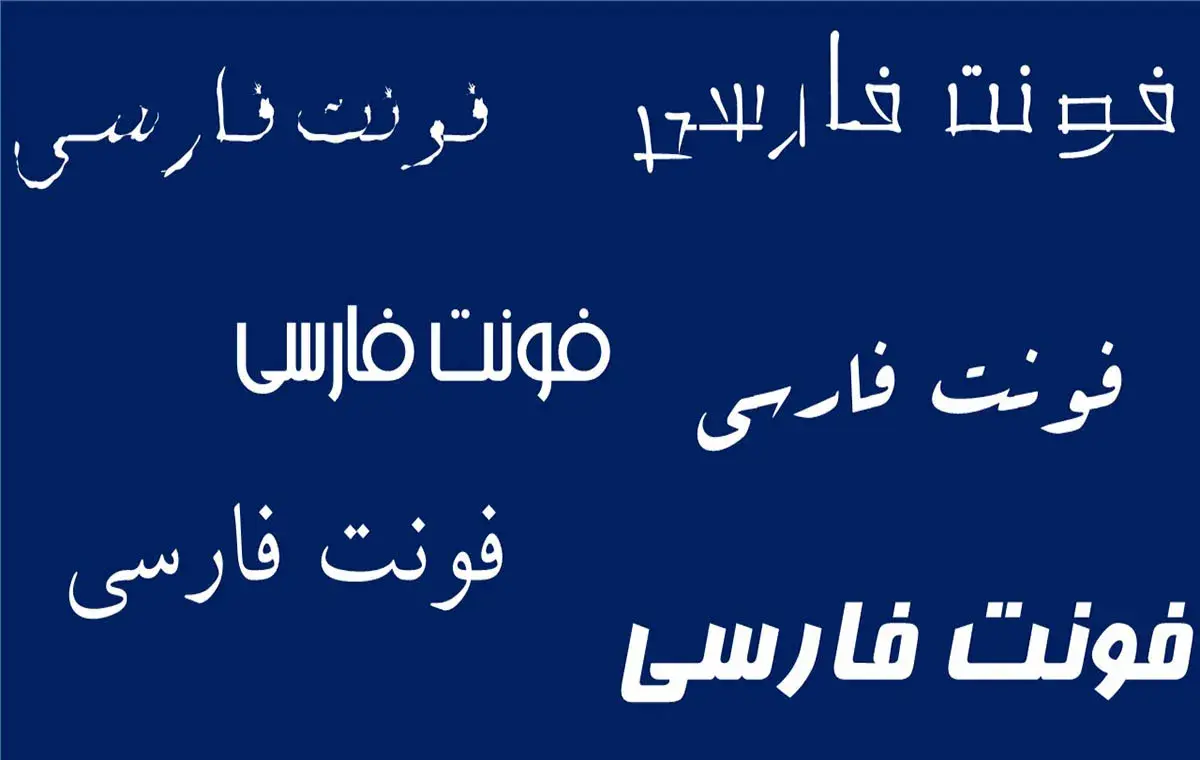
بهترین فونتهای فارسی برای تولید محتوا
برای موفقیت در تولید محتوای فارسی، توجه به جزئیاتی مانند فونت اهمیت زیادی دارد؛ زیرا فونت مناسب نهتنها بر زیبایی ظاهری محتوا تأثیر میگذارد، بلکه در درک بهتر پیام، جذب مخاطب و ایجاد اعتماد نیز نقش دارد. فونتهایی مانند «وزیر»، «ایرانسنس» و «شبنم» از گزینههای رایگان و پرکاربردی هستند که به دلیل طراحی مدرن، خوانایی بالا و سازگاری با محتوای دیجیتال، محبوبیت زیادی یافتهاند. در ادامه مطلب، فهرستی از بهترین فونتهای فارسی برای تولید محتوا با کاربردهای مختلف ارائه شده تا کاربران بتوانند با دقت و آگاهی، فونتی متناسب با پیام محتوای خود انتخاب کنند.
معیارهای انتخاب بهترین فونتهای فارسی برای تولید محتوا
در فرآیند تولید محتوای فارسی، انتخاب فونت از آن دسته تصمیماتی است که در ظاهر ساده به نظر میرسد، اما در عمل تاثیر بسیار عمیقی بر کیفیت نهایی محتوا و تجربه مخاطب میگذارد. فونت نقش به سزایی در زیباییشناسی، ارتباطی و حتی روانی مخاطب دارد. بسیاری از مخاطبان قبل از آنکه مفهوم متن را درک کنند، ناخودآگاه با ظاهر آن ارتباط برقرار میکنند. بنابراین فونتی که انتخاب میکنید باید بتواند بهدرستی و با دقت، روح و لحن محتوای شما را بازتاب دهد.
یکی از اساسیترین معیارهای انتخاب فونت، وضوح و خوانایی بالا است. در دنیایی که کاربران اغلب با چشم خسته، در محیطهای پرنور یا با اسکرینهای کوچک در حال مطالعه هستند، فونتی که ساختار واضح، ضخامت مناسب خطوط، فاصله مناسب بین حروف و سطرها و چشمنواز بودن را داشته باشد، مزیتی بزرگ محسوب میشود. فونتهایی که بیش از حد تزئینی، فشرده یا سبک هستند، حتی اگر زیبا باشند ممکن است باعث رها شدن متن شوند.
معیار مهم بعدی، هماهنگی سبک فونت با محتوای ارائهشده است. مثلا اگر در حال نگارش یک مقاله علمی، خبری یا حقوقی هستید، فونتی با فرم رسمی و متقارن که حس اعتماد و جدیت القا میکند، بهترین انتخاب است. اما اگر محتوای شما آموزشی، سرگرمکننده یا روزمره باشد، فونتی با ساختار سادهتر، منحنیهای ملایمتر و حالوهوای خودمانیتر، تعامل بهتری با مخاطب ایجاد خواهد کرد. این تطابق ظریف میان سبک نوشتاری و شکل نوشتار، اغلب نادیده گرفته میشود اما تاثیر مهمی بر ماندگاری برند یا پیام دارد.
علاوه بر این، فونت انتخابی شما باید در فضاهای مختلف به درستی عمل کند. این یعنی چه در موبایل، چه در تبلت، چه در مانیتورهای بزرگ، فونت دچار شکستگی، جابهجایی یا تغییر ساختاری نشود. همچنین اگر محتوا قرار است چاپ شود، باید از فونتی استفاده شود که در نسخه چاپی هم کیفیت، نظم و خوانایی لازم را حفظ کند. نکتهای که در فضای دیجیتال بسیار مهم است، عملکرد فونت در حجمهای بالا و در فواصل طولانی متن است. برخی فونتها در عناوین خوب بهنظر میرسند اما در پاراگرافهای طولانی خستهکنندهاند.
نکته قابل توجه دیگر، هویت بصری برند یا محتوا است. فونت بخشی از شخصیت گرافیکی شماست. اگر تولید محتوای شما در بستر مشخصی انجام میشود ـ مثلا یک پیج اینستاگرامی با لحن خاص یا یک وبسایت رسمی ـ بهتر است فونتی را انتخاب کنید که با بقیه عناصر گرافیکی شما مثل رنگها، آیکونها و حتی لوگو همخوانی داشته باشد. یک فونت هماهنگ، باعث انسجام تصویری میشود و مخاطب را ناخودآگاه به برند یا محتوای شما وفادارتر میکند.
همچنین نباید از اهمیت جزئیات طراحی فونت غافل شد. کیفیت خط کرسی، دقت در طراحی حروف خاص فارسی مانند «ک» و «ی»، شکل نقطهها، نحوه اتصال حروف و حتی وضعیت کشیدهنویسی یا نسخههای بولد و نازک، همه در تاثیرگذاری بصری آن نقش دارند. فونتی که از نظر طراحی حروف متعادل و دقیق باشد، میتواند به افزایش تمرکز خواننده کمک کند و انتقال پیام را به شکل کاملتری انجام دهد.
در کنار این نکات، انتخاب فونت باید بر پایه تجربه کاربری واقعی صورت بگیرد، نه فقط ظاهر اولیه آن. گاهی ممکن است فونتی در نگاه اول جذاب باشد، اما وقتی در متنهای طولانی یا در انواع تیتر و زیرتیتر استفاده شود، مشکلاتی مانند سنگینی بصری، تکرار خستهکننده یا سختخوان بودن را نشان دهد. بنابراین پیش از انتخاب نهایی، بهتر است فونت را در کاربردهای واقعی امتحان کنید.
در نهایت باید گفت که فونت، بخشی از زبان تصویری محتواست. همانطور که نوع جملهبندی، لحن و سبک نوشتاری شما حامل پیام است، شکل و فرم نوشتار هم پیام مستقلی دارد. فونتی که با دقت انتخاب شده باشد، میتواند حس اعتماد، صمیمیت، هیجان یا حتی آرامش را منتقل کند؛ بدون آنکه حتی یک کلمه حرف بزند. انتخاب درست فونت، یک مهارت مهم در طراحی محتواست که نیاز به دقت، سلیقه و شناخت دقیق از هدف محتوا و مخاطب دارد.
بهترین فونتهای فارسی برای تولید محتوا؛ وزیر
فونت وزیر یکی از معروفترین و بهترین فونتهای فارسی برای تولید محتوا است که توسط مرحوم صابر راستی کردار طراحی شده است. این فونت با الهام از فونتهای مدرن لاتین طراحی شده و ویژگی بارز آن، سادگی و نظم در ساختار حروف است. در فونت وزیر، هر حرف جای خودش را بهخوبی پیدا کرده است؛ فاصلهها استاندارد هستند و خوانایی آن در ابعاد مختلف بسیار بالاست. یکی از مزایای مهم وزیر این است که در صفحات وب بهخوبی رندر میشود و به همین دلیل در بسیاری از وبسایتهای حرفهای، بلاگها و صفحات طولانی محتوایی از آن استفاده میشود. این فونت از نسخههای نازک تا ضخیم پشتیبانی میکند و در تایپوگرافی دیجیتال، قدرت انعطاف بالایی دارد. حتی در استفاده در نرمافزارهای آفیس یا فتوشاپ هم عملکرد بسیار خوبی دارد.
بهترین فونتهای فارسی رایگان برای تولید محتوا؛ شبنم
فونت شبنم از دیگر گزینههای رایگان و قابل اتکا در فضای تایپ فارسی است. طراحی آن کمی رسمیتر و سنگینتر از وزیر است، اما همچنان حال و هوای مدرن دارد. شبنم بهخصوص در تیترها عالی عمل میکند؛ حروف آن کمی پهنتر و ضخیمتر هستند و در سایزهای بزرگتر بهتر به چشم میآید. این فونت ترکیبی از رسمی بودن و صمیمیت را در دل خود دارد، به همین دلیل در طراحی وب، مجلات دیجیتال، بروشورها و حتی اینفوگرافیها میتواند انتخاب خوبی باشد. از آنجایی که شبنم تعادل مناسبی میان فرم و خوانایی دارد، میتوان آن را در هر دو حالت چاپی و دیجیتال با خیال راحت استفاده کرد.
بهترین فونتهای فارسی برای تولید محتوا؛ صمیم
فونت صمیم از نظر احساسی یکی از دلپذیرترین فونتهای فارسی است. خطوط منحنی، گوشههای گرد و فضای باز بین حروف، باعث شده این فونت حس نزدیکی و راحتی را منتقل کند. اگر در حال تولید محتوایی هستید که قرار است رابطهای دوستانه با مخاطب ایجاد کند، مثلا محتواهای آموزشی، خانوادگی، کودکمحور یا شبکههای اجتماعی، فونت صمیم انتخاب فوقالعادهای است. این فونت در اپلیکیشنهای موبایلی هم بهخوبی عمل میکند چون فرم آن برای مطالعهی طولانی مناسب است و در نمایشگرهای کوچک هم خواناست. صمیم نشان میدهد که فونت فقط مسئلهی زیبایی نیست، بلکه میتواند در لحن محتوا هم تاثیرگذار باشد.
بهترین فونتهای فارسی برای تولید محتوا؛ ساحل
فونت ساحل ساختاری شبیه به شبنم دارد، اما از نظر بصری کمی سبکتر است. این فونت نه خیلی رسمی است و نه خیلی خودمانی؛ یک تعادل کاربردی برای موقعیتهای مختلف دارد. از آن در طراحی سایت، ارائههای رسمی، محتوای شرکتی یا حتی طراحی بروشورها میتوان استفاده کرد. ویژگی مهم ساحل، ظاهر تمیز و ساده آن است. از آنجایی که حروف این فونت زاویهدارتر و دقیقتر طراحی شدهاند، برای پروژههایی که دقت و نظم بصری مهم است، گزینه خوبی خواهد بود. در عین حال، ضخامت مناسب خطوط آن اجازه میدهد تا در تیترهای واضح یا متون برجسته هم از آن بهره گرفت.
بهترین فونتهای فارسی برای تولید محتوا؛ دیناربیک
فونت دیناربیک یکی از فونتهایی است که ظاهری امروزی و سیستماتیک دارد. ساختار این فونت مستطیلیتر است و از خطوط صاف و شکسته بیشتری استفاده میکند. در نتیجه، فرمی مهندسیوار و فنی به خود گرفته که برای پنلهای مدیریتی، رابط کاربری وبسایتها، داشبوردهای دیجیتال یا هر محیطی که نیاز به نمایش دقیق اطلاعات وجود دارد، عالی عمل میکند. دیناربیک همچنین در پروژههایی که با داده، آمار یا تکنولوژی سر و کار دارند، حس مدرنیته و نظم را منتقل میکند. طراحی حروف آن بهگونهایست که در محیطهای پرمحتوا با فونت کوچک همچنان شفاف و قابل خواندن باقی میماند.
بهترین فونتهای فارسی برای تولید محتوا؛ ایران یکان
فونت ایران یکان و نسخههای مشابه آن هم از جمله فونتهایی هستند که فرم خاص خود را دارند. این فونت مینیمال، ساده و بسیار مدرن طراحی شده و در برندهای حرفهای، اپلیکیشنهای موبایل و طراحیهای گرافیکی بهشدت کاربرد دارد. ویژگی بارز آن، عدم استفاده از تزئینات اضافی، فاصلههای متوازن و یکدستی بالا بین خطوط و حروف است. فونتهای رایگان مشابه ایرانیکان هم از همین اصول طراحی پیروی میکنند و اگرچه بعضا در کیفیت به آن نمیرسند، اما برای پروژههایی که نمیخواهند هزینه پرداخت کنند، جایگزینهای خوبی به حساب میآیند. این سبک فونت برای کسبوکارهای استارتاپی، فروشگاههای آنلاین و رابطهای کاربری دیجیتال، ایدهآل است.
بهترین فونتهای فارسی برای تولید محتوا؛ نوتو
فونت نوتو نسخ فارسی توسط گوگل منتشر شده و یکی از فونتهای بسیار سبک، منظم و خواناست. طراحی آن بر اساس شیوهی سنتی نسخ انجام شده، اما برای استفاده در محیطهای دیجیتال بهینهسازی شده است. از آنجایی که گوگل پشت این فونت است، میتوان از سازگاری بالا، اجرای روان در مرورگرها و وضوح بینقص آن مطمئن بود. در متون طولانی، مقالات علمی، سایتهای خبری یا بخشهای بلاگ بسیار عملکرد خوبی دارد و چون از نظر فنی بسیار سبک است، در صفحات پرمحتوا باعث افزایش سرعت لود هم خواهد شد.
بنان
فونت بنان را میتوان یکی از فونتهای خاص و خلاقانه در تایپ فارسی دانست. حروف این فونت حالتی هنری دارند و با خلاقیت طراحی شدهاند، بهطوریکه حالت هندسی و حتی کمی نامتعارف دارند. بنان برای محتواهایی که دنبال تمایز هستند کاربرد دارد: مثلا طراحی جلد کتاب، پوسترهای کودکانه یا طرحهایی که قرار است حس کنجکاوی، شور یا هیجان را منتقل کنند. البته استفاده مداوم از آن در متنهای زیاد توصیه نمیشود، چون ممکن است چشم را درگیر و ذهن را از محتوا دور کند، اما برای طراحی بصری و نوآورانه جای خود را دارد.
نیریزی
فونت نیریزی یکی از فونتهای خاص و خوشساخت در میان فونتهای فارسی است که بر پایهی زیباییهای خوشنویسی نسخ و ثلث طراحی شده است. حروف در این فونت بلند، کشیده و پر از جزئیاتاند. ضخامتها در آن متغیر هستند و حرکت خطی حروف حالتی شبیه به نوشتار سنتی دارد. نیریزی بهویژه در پروژههایی کاربرد دارد که میخواهند حس رسمی، تاریخی یا فرهنگی منتقل کنند. اگر در حال طراحی بروشورهای مذهبی، بنرهای فرهنگی یا مقالات با لحن جدی هستید، این فونت با جلوهی سنگین و رسمیاش انتخابی هنرمندانه خواهد بود. البته استفاده از آن در متنهای طولانی دیجیتال توصیه نمیشود، چرا که بیش از اندازه جلوه دارد و تمرکز مخاطب را از محتوا دور میکند.
فرهود
فونت فرهود ترکیبی از صراحت و ظرافت است. طراحی آن بهنوعی میان فونتهای چاپی قدیمی و تایپهای مدرن فارسی ایستاده به حساب میآید. حروف در این فونت حالتی نرم دارند، اما در عین حال رسمالخط آن دارای ساختار استوار است. فرهود بیشتر در پروژههایی کاربرد دارد که به دنبال یک بیان ادبی یا فرهنگیاند؛ مثلا در صفحات کتاب، جلد رمانها، بروشورهای فرهنگی یا محتوای مرتبط با ادبیات و تاریخ. این فونت حس احترام، وقار و دقت را به خواننده منتقل میکند و اگر با فاصلهگذاری مناسب استفاده شود، میتواند تجربهی خواندن دلپذیری هم فراهم کند.
ایرانسنس
فونت ایرانسنس یکی از مشهورترین و پراستفادهترین فونتهای فارسی مدرن در سالهای اخیر است. این فونت بهصورت رسمی پولی است، اما نسخههایی از آن در دسترس عموم قرار گرفته است. حروف این فونت کاملا امروزی، فشرده، ساده و خوانا هستند. طراحی آن برای محیطهای دیجیتال بهینه شدهاند و در اکثر وبسایتهای بزرگ ایرانی از آن استفاده میشود. ایرانسنس حس برندینگ، نوآوری، مینیمالیسم و جدیت را با هم دارد. در سایتهای خبری، اپلیکیشنها، پلتفرمهای آموزشی و هر جایی که مخاطب حرفهای حضور دارد، میتوان این فونت را دید. بدون اغراق میتوان گفت ایرانسنس به استاندارد جدیدی در تایپوگرافی فارسی تبدیل شده است.
انجمن
فونت انجمن از نظر زیباییشناسی تلفیقی از خطوط تیز، خطوط شکسته و سبک نوشتاری خاص است. در نگاه اول، فونت انجمن یک حس سنتی اما جسور را منتقل میکند. حروف در آن کشیده، کمی ناصاف و پر از انرژیاند؛ همین باعث شده تا انجمن بیشتر برای تیترها، بنرهای فرهنگی، یا پوسترهایی با لحن اجتماعی یا سیاسی استفاده شود. اگر به دنبال فونتی هستید که نوعی جدیت پرحرارت را منتقل کند، انجمن انتخاب متفاوتی خواهد بود. البته در بدنهی متن استفاده از آن کمتر رایج است، چون فرم خاصش در طولانیمدت چشم را خسته میکند. همچنین این فونت رایگان نیست و اگر تمایل به استفاده از آن دارید باید فونت انجمن را خریداری کنید.
لالهزار
فونت لالهزار به عنوان یکی از فونتهای نمایشی و بسیار شاخص فارسی شناخته میشود که طراحی آن از تئاتر، سینما و هنر دهههای گذشته ایران برگرفته شده است. ساختار ضخیم، حروف ایستاده و حضور پررنگ تزئینات در طراحی، لالهزار را تبدیل به فونتی کرده که جلب توجه میکند. این فونت نه برای خواندن طولانی، بلکه برای دیده شدن ساخته شده است. در طراحی پوسترهای نمایشی، بنرهای تبلیغاتی، جلد مجلههای هنری یا طراحیهای نوستالژیک میتواند تاثیرگذار باشد. لالهزار با وجود خاصبودنش، بهخاطر رایگانبودن در بین طراحان بسیار محبوب شده است.
ایرانمارکر
فونت ایرانمارکر فونتی خلاقانه و غیررسمی است. فرم حروف آن طوری طراحی شده که گویی با ماژیک نوشته شدهاند. این نوع طراحی، حس خودمانی و پرانرژی دارد. ایرانمارکر برای تولید محتوا در فضای کودکانه، جوانپسند، آموزشی یا هنری بسیار مناسب است. مخصوصا در طراحی استوریهای اینستاگرام، کاور ویدیوها یا محتوای آموزشی برای نوجوانان میتواند جلب توجه کند. ویژگی مهم آن، انعطافپذیری بالای آن در جلب توجه مخاطب در یک نگاه است. البته در متنهای رسمی یا پروژههای سازمانی جایی ندارد.
اردیبهشت
فونت اردیبهشت از آن فونتهایی است که ظاهر زیبا و ترکیبی آن از سنت و مدرنیته را نمیتوان نادیده گرفت. ساختار حروف در آن نرم، خمیده و بسیار چشمنواز است. اردیبهشت فونتیست که با احساس کار میکند. بیشتر برای پروژههای شاعرانه، هنری، فرهنگی یا حتی صفحات اول کتابهای رمان و شعر استفاده میشود. این فونت بهخاطر جلوه هنریاش برای تیترها بسیار مناسب است. استفاده بیش از حد از آن در پاراگرافهای بلند ممکن است باعث افت خوانایی شود، اما در بخشهای تاکیدی متن بهخوبی میدرخشد.
سخن پایانی
فونت، در واقع شخصیت نوشته شماست. همانطور که یک لباس مناسب میتواند ظاهر فرد را حرفهایتر جلوه دهد، بهترین فونتهای فارسی برای تولید محتوا هم متن شما را حرفهای، خوانا و دلنشینتر میکند. تفاوتی ندارد که در حال طراحی پست برای شبکههای اجتماعی هستید، یک مقاله وبسایتی مینویسید یا حتی ویدیویی آموزشی میسازید؛ در همه این موارد، انتخاب فونت فارسی مناسب، میتواند ارتباط مخاطب را متحول کند. بهویژه در زبان فارسی، با تنوع بالای فونتها، انتخاب صحیح نهتنها یک مزیت بلکه یک ضرورت است.
فونتهای معرفی شده تنها گوشهای از دنیای غنی تایپ فارسی هستند، اما هرکدام ویژگیها و کاربردهای خاص خود را دارند. آشنایی دقیق با این خصوصیات میتواند شما را در انتخابی آگاهانه یاری کند تا نهتنها از نظر زیباییشناسی، بلکه از لحاظ کاربردی نیز بهترین تجربه را برای مخاطب فراهم سازید. برای بررسی فونتهای بیشتر و نمونههای دیگر، پیشنهاد میشود منابع و گالریهای تخصصی فونت فارسی را مرور کنید تا با گزینههای متنوعتری هم آشنا شوید.